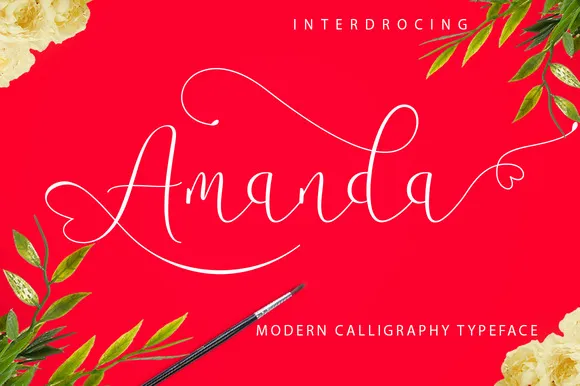
A Amanda Script Font é uma escolha perfeita para quem busca um estilo elegante e sofisticado. Com sua linha suave, traços clássicos e toques refinados, esta fonte de calligrafia traz à tona o gesto natural da escrita em seu design único e versátil. Ideal tanto para trabalhos profissionais como para criações mais criativas, a Amanda Script é uma escolha ideal para branding, embalagens ou qualquer outro projeto que exige um toque de elegância. Suave e sofisticada, ela se adequa perfeitamente à sua necessidade de criar design projetos com estilo autêntico e único. Seja qual for seu objetivo visual, a Amanda Script pode ser o elemento chave para revolucionar seus designs.